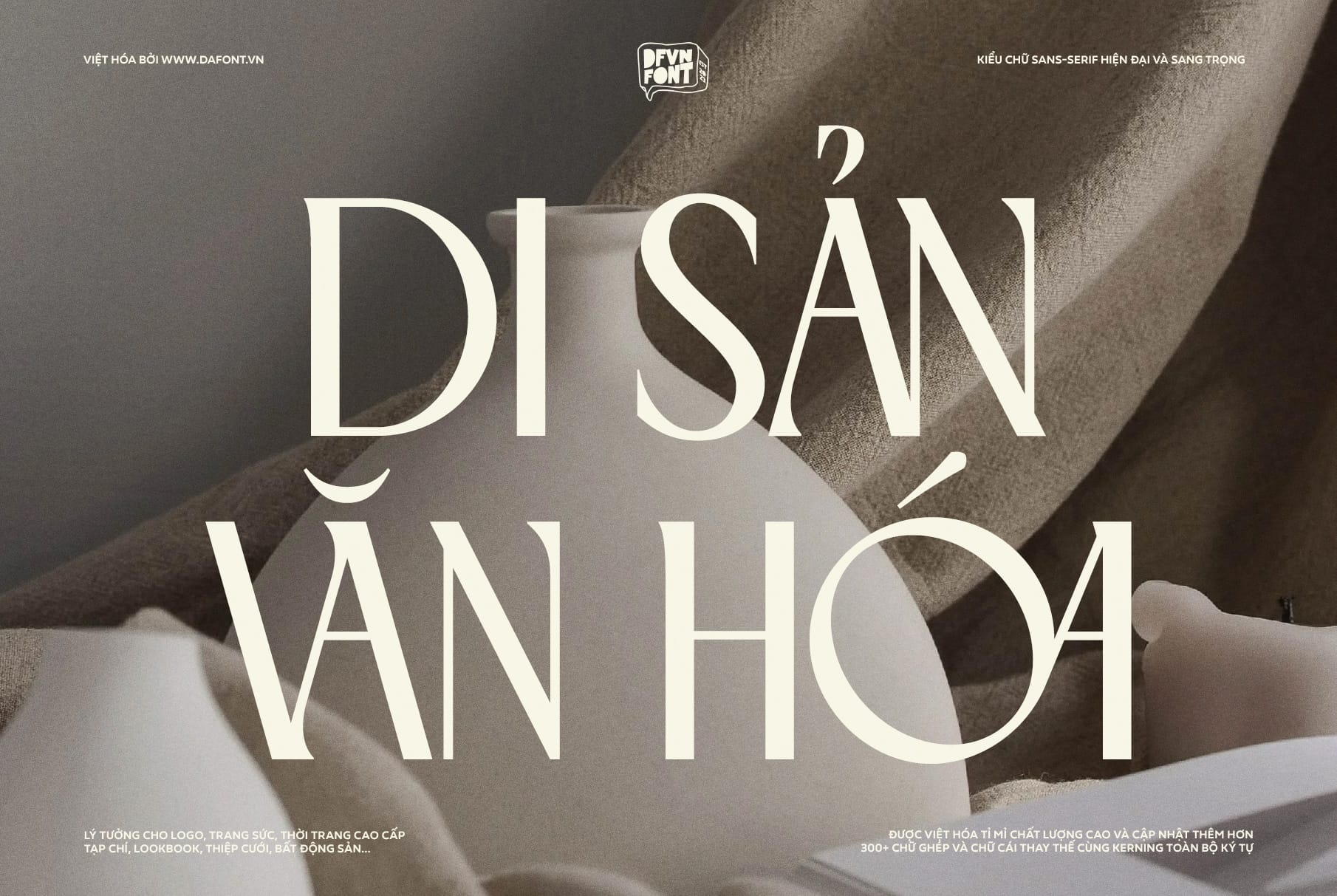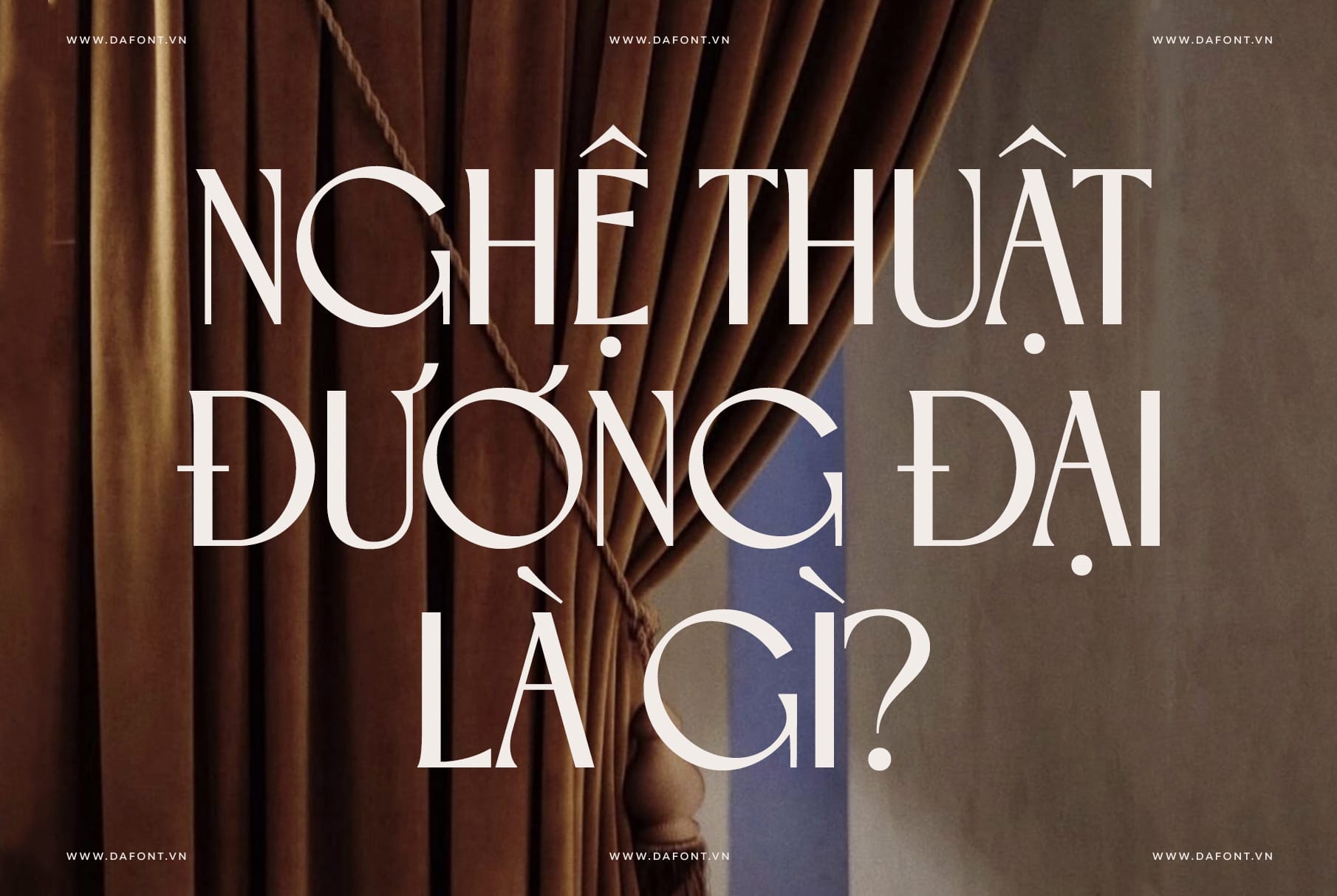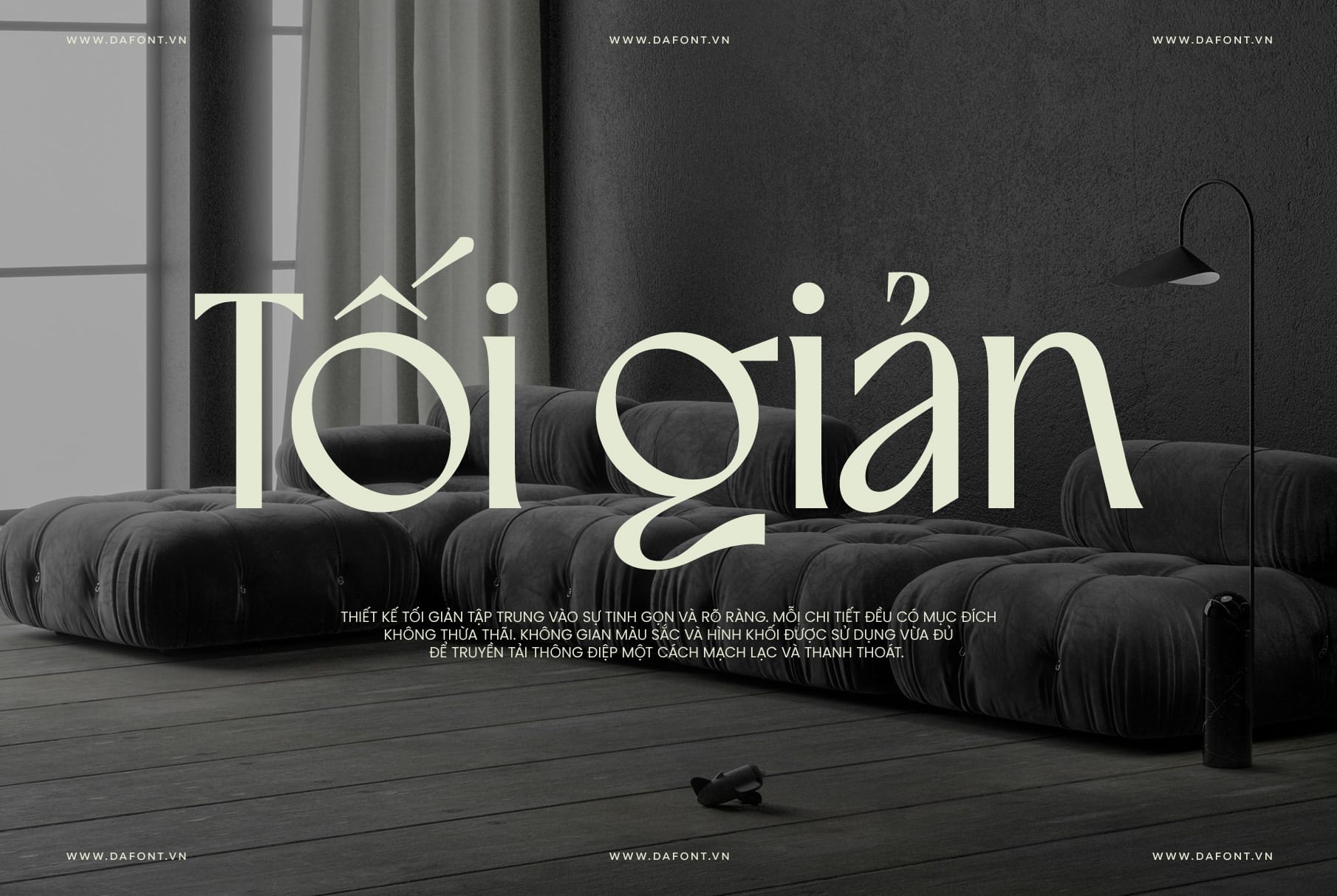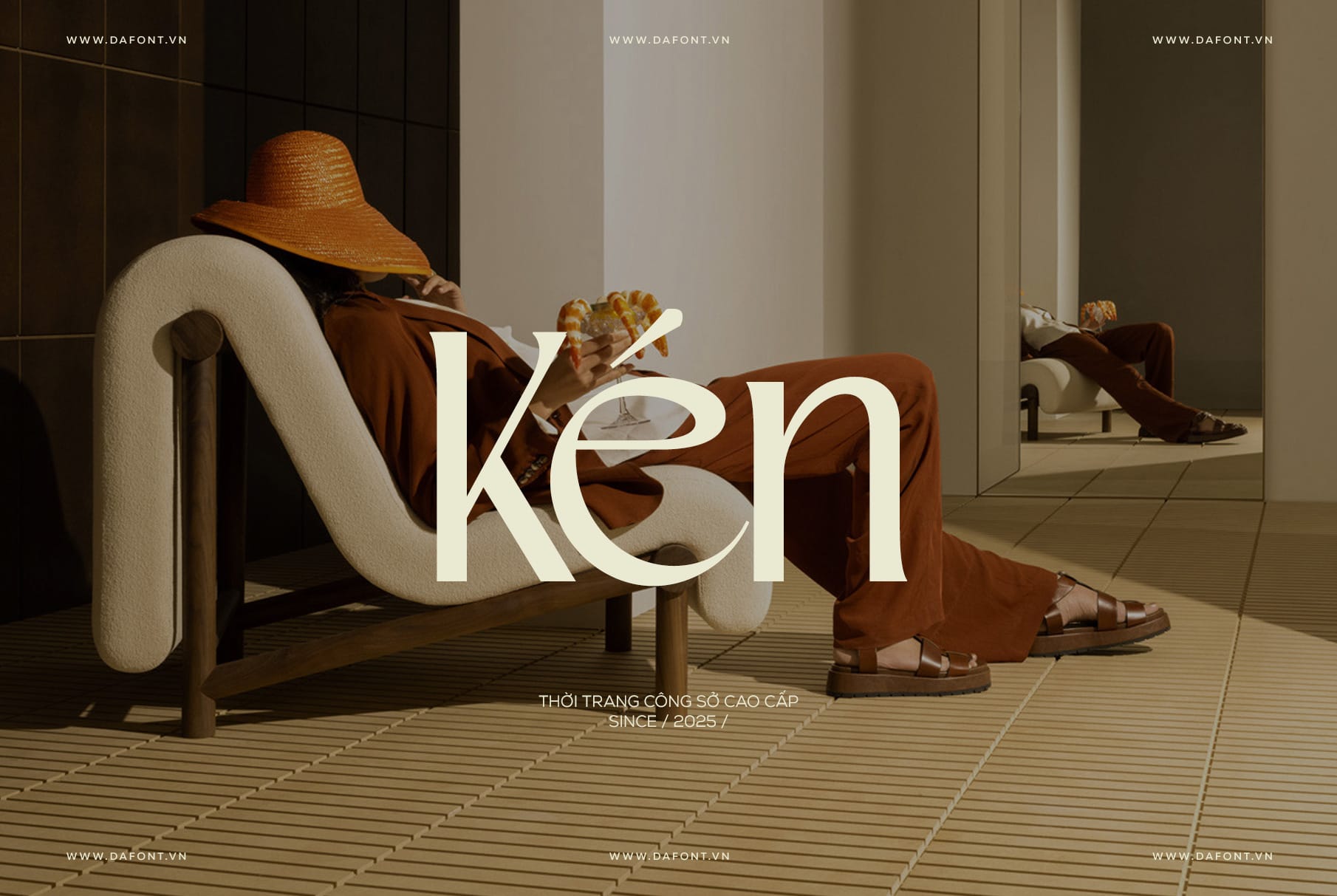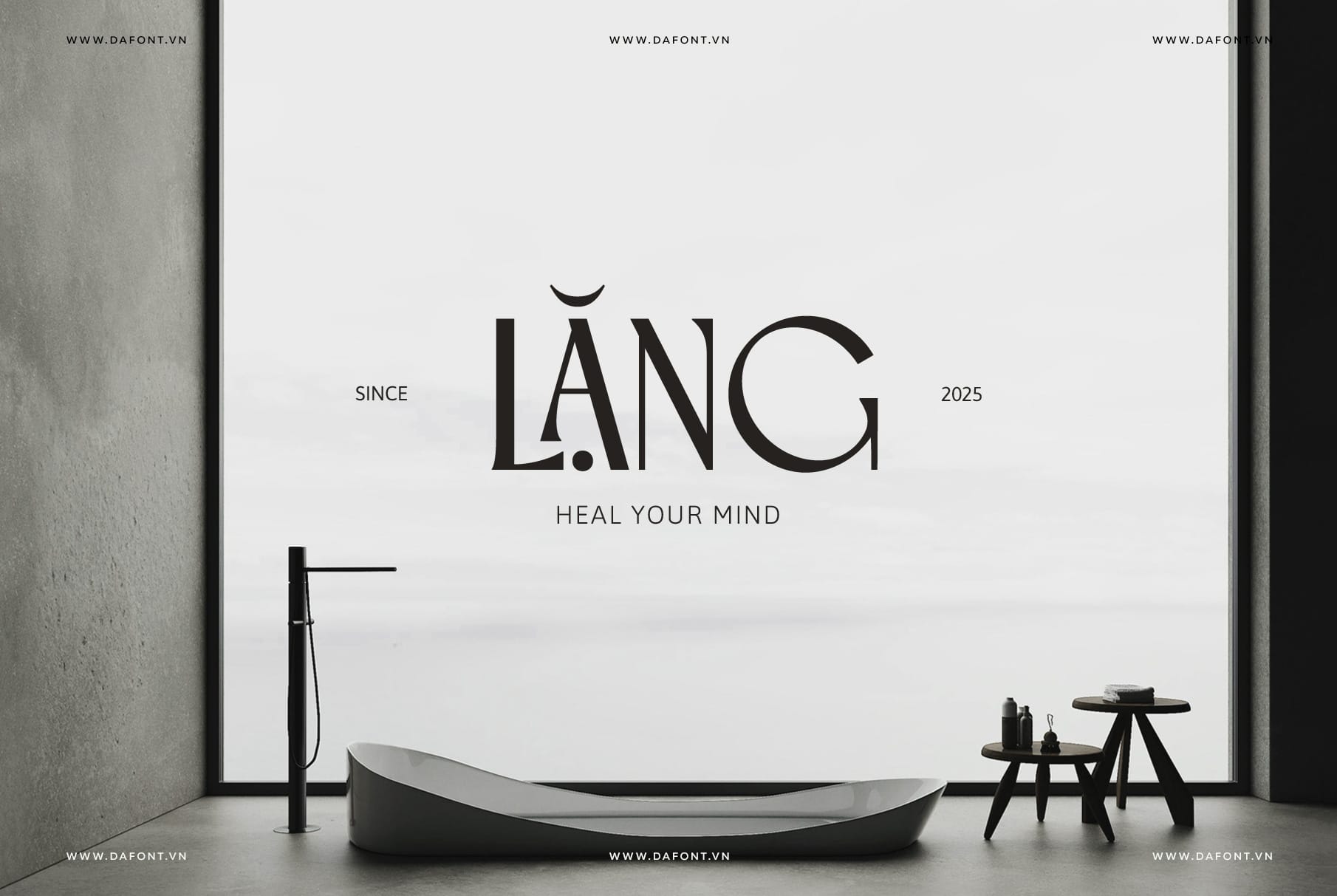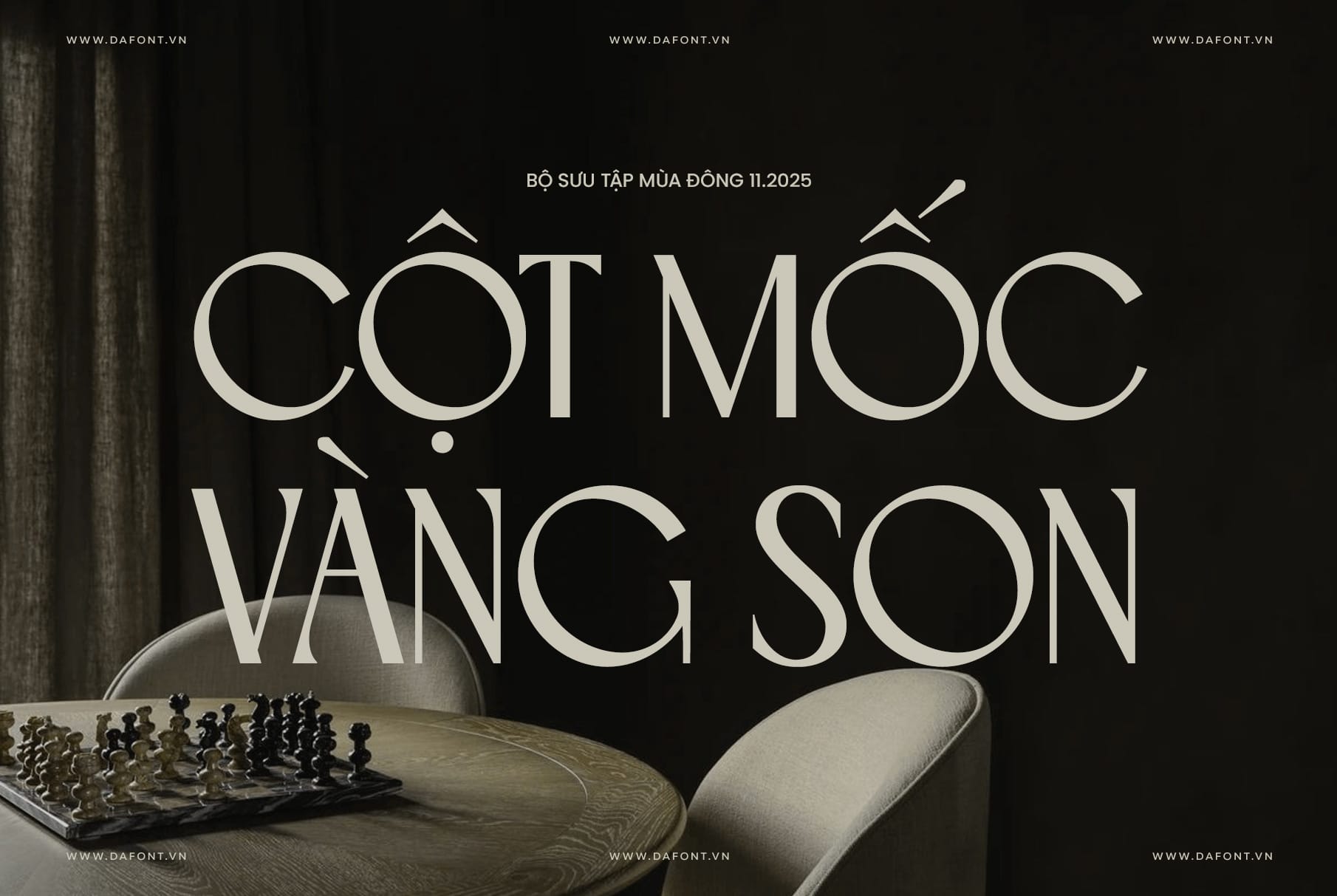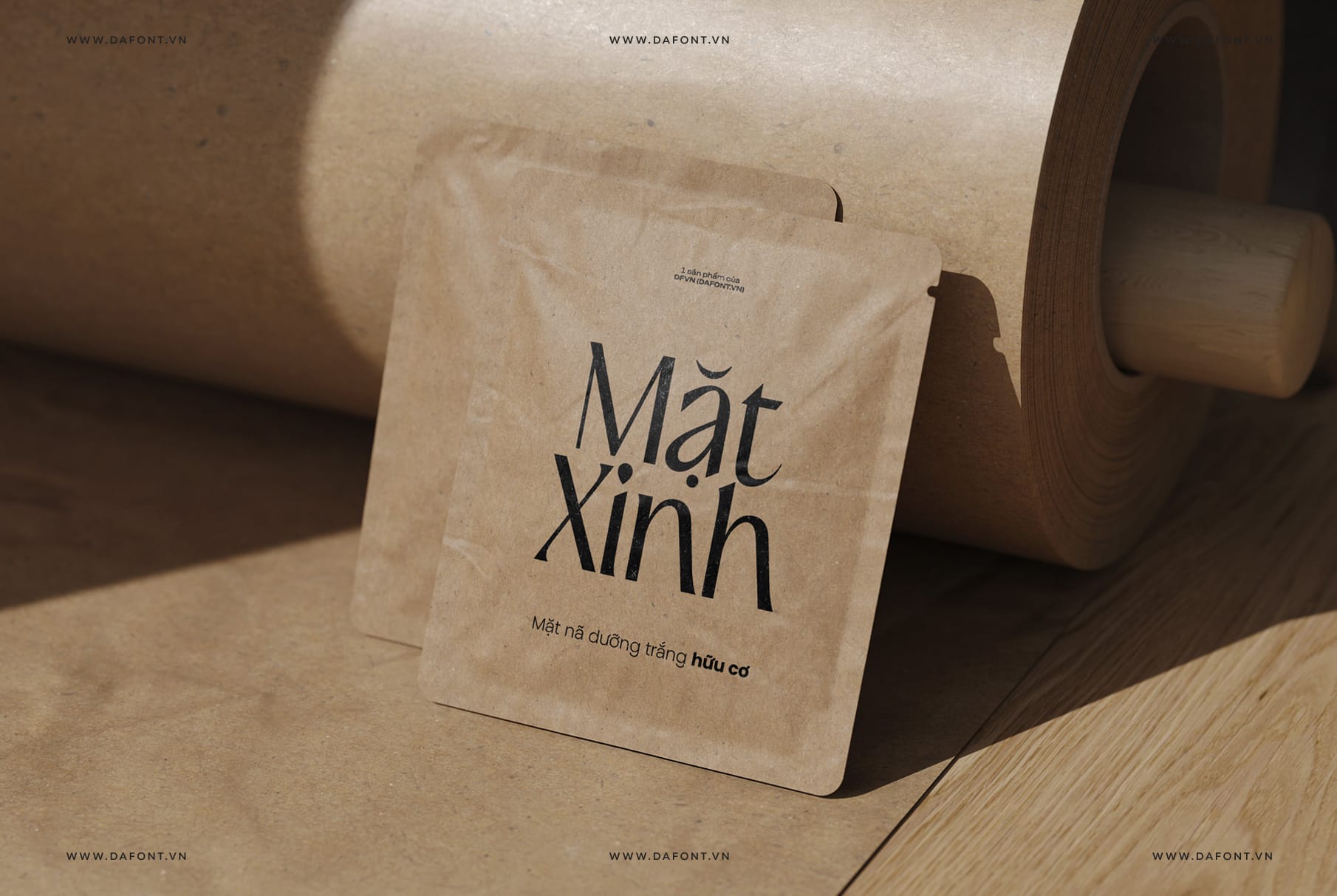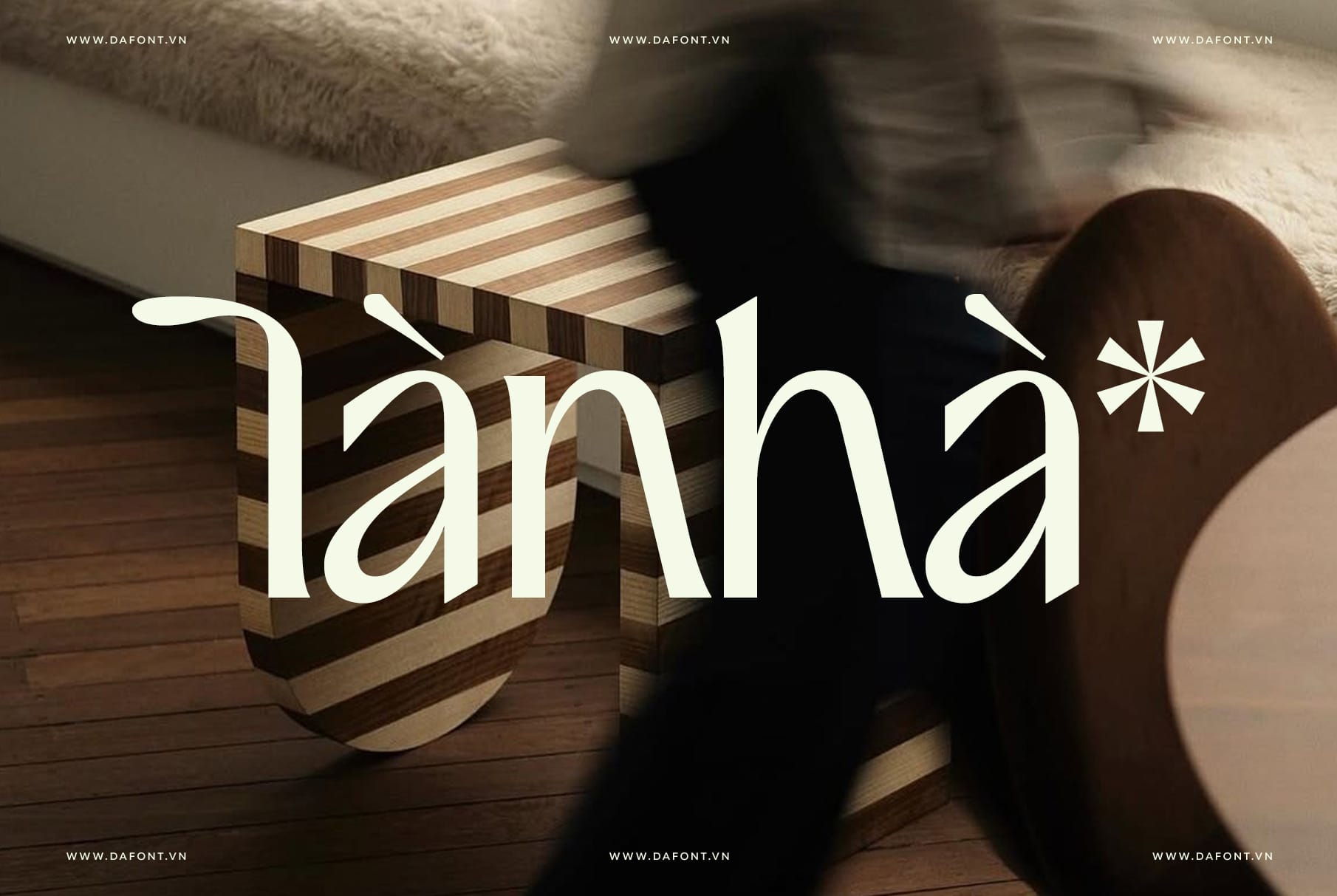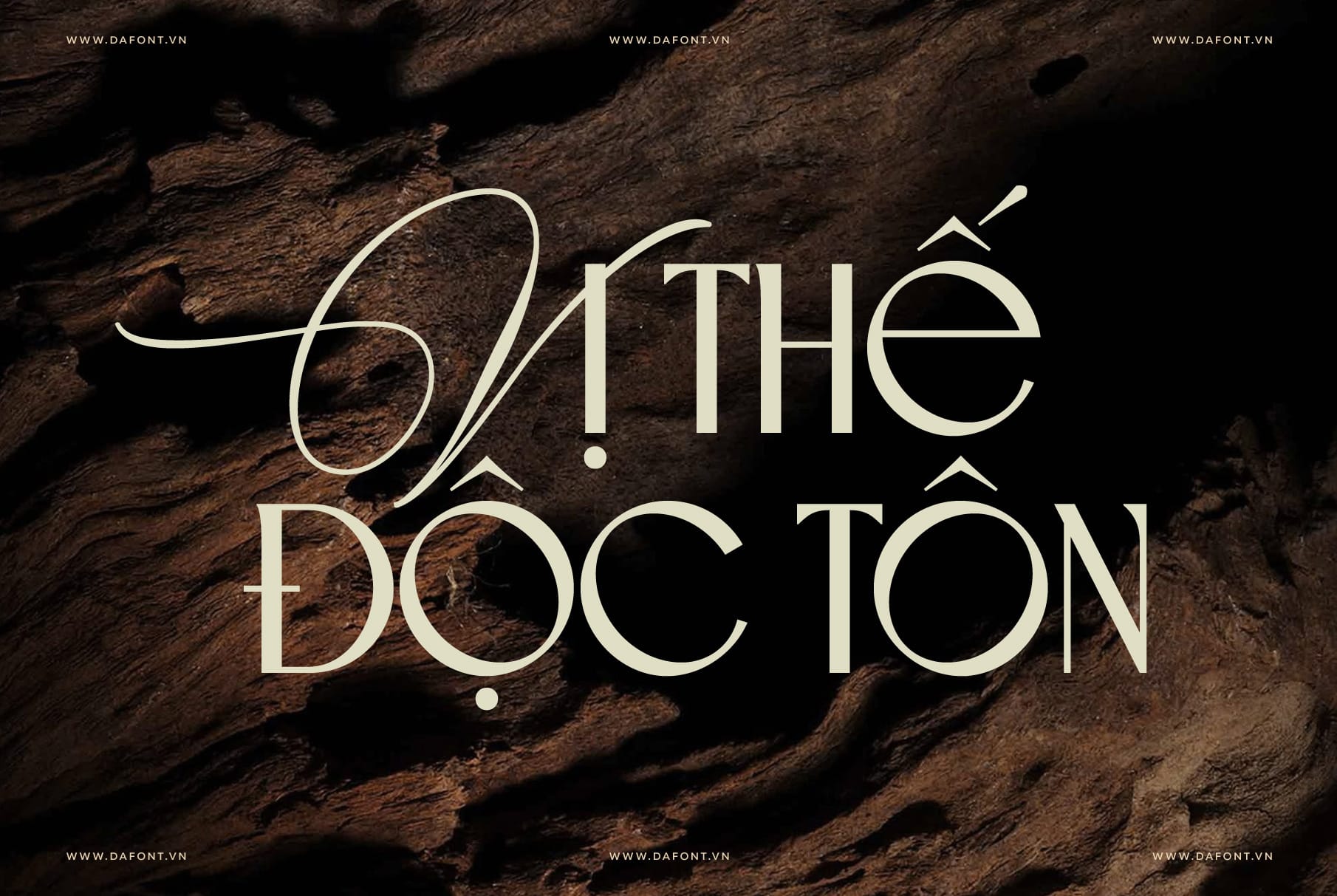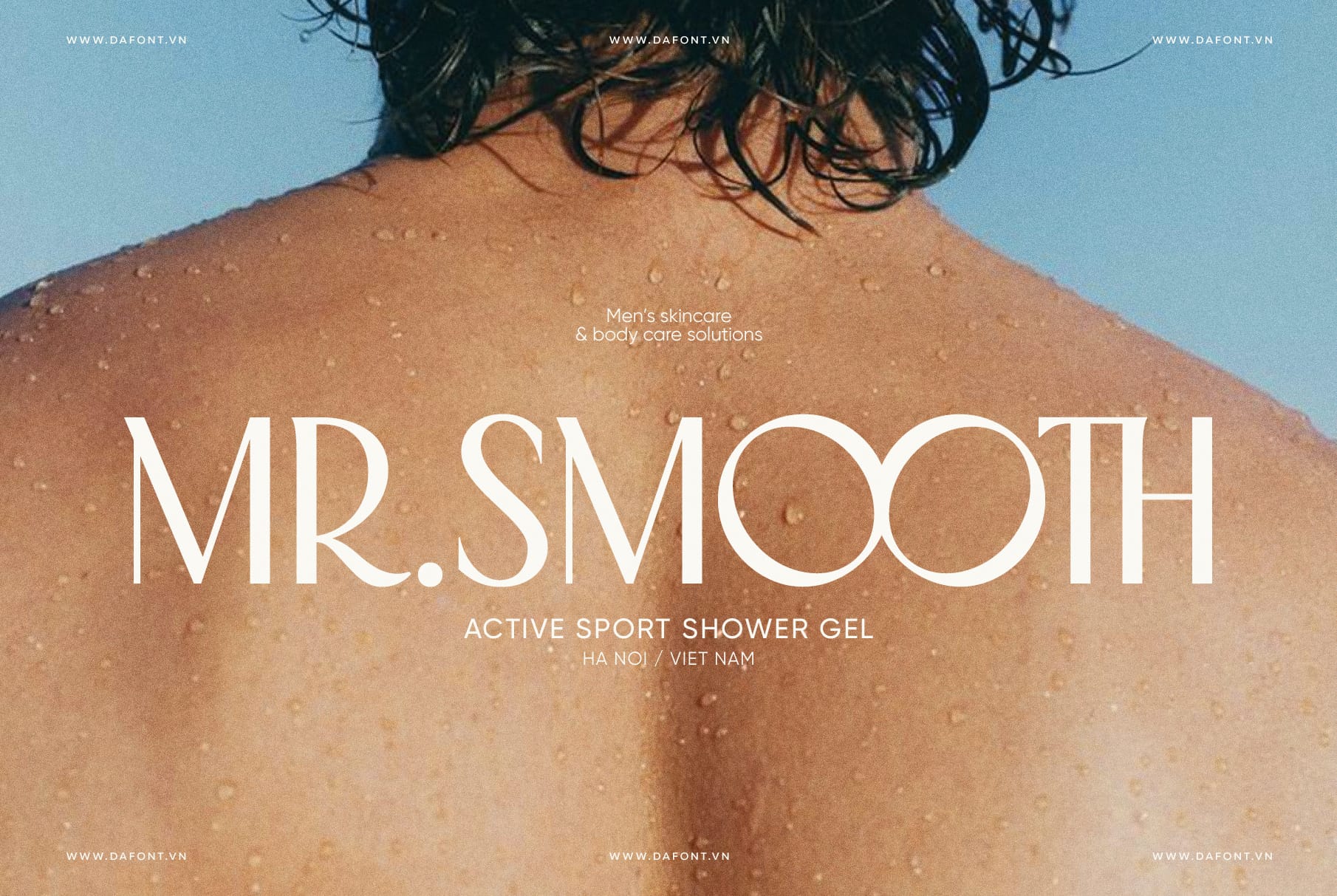
DFVN Soleá là một sans serif typeface kết hợp hoàn hảo giữa thiết kế tối giản, độ tương phản tinh tế và những chi tiết hiện đại, khiến nó trở thành lựa chọn hàng đầu cho các dự án luxury branding, editorial design và logo cao cấp. Với hơn 300+ ligatures, stylistic alternates phong phú và khả năng hỗ trợ đa ngôn ngữ, DFVN Soleá mang đến sự linh hoạt vượt trội, phù hợp cho nhiều dự án thiết kế khác nhau.
Đặc điểm nổi bật DFVN Soleá
1. Tinh thần tối giản nhưng vẫn cá tính
Điểm thú vị của Soleá nằm ở việc nó không cố gắng gây ấn tượng bằng sự ồn ào. Các chữ cái được vẽ với cấu trúc tối giản, tỉ lệ thanh – đậm vừa phải, tạo cảm giác gọn gàng. Tuy nhiên, ở những ký tự như “a”, “e”, “s” hay các chữ có dấu móc, người thiết kế khéo léo đưa vào những đường cong mềm, các chi tiết bất đối xứng nhẹ, khiến font vừa thanh lịch vừa có “cá tính thương hiệu”.
Nhờ đó, DFVN Soleá không bị “lẫn” trong hàng ngàn font chữ sans serif khác trên thị trường, mà vẫn giữ được độ nghiêm túc cần có cho các thương hiệu cao cấp.
2. Hệ thống ligature & stylistic alternates phong phú
Soleá nguyên bản đi kèm hơn 55 ligature và glyph thay thế. Ngoài ra, DFVN đã cập nhât và Việt hóa thêm hơn 300 chữ ghép và biến thể ký tự khác. Đây là yếu tố đặc biệt quan trọng đối với các nhà thiết kế làm việc trong lĩnh vực branding hoặc editorial, bởi vì:
- Bạn có thể tạo logo wordmark độc quyền chỉ bằng cách kết hợp chữ cái với các ligature có sẵn.
- Headline, title tạp chí, bìa lookbook, cover catalogue dễ dàng trở nên “editorial” và giàu tính thời trang hơn.
- Khi sử dụng cho poster hoặc social media, chỉ cần thay đổi một vài glyph là đã có một bố cục mang cảm giác “bespoke” (thiết kế riêng), không giống font hệ thống.
Hệ thống stylistic sets cũng giúp người dùng tùy chỉnh mức độ “phá cách” của font, từ an toàn – tinh gọn cho tới sắc sảo – đậm chất thời trang.
3. Việt hóa chất lượng cao
DFVN Soleá được Việt hóa một cách tỉ mỉ, với hệ thống ký tự được căn chỉnh cẩn thận để đảm bảo tính thẩm mỹ và khả năng đọc tối ưu. Bộ chữ bao gồm hơn 300 ký tự thay thế và chữ ghép đã được Việt hóa đầy đủ, giúp mở rộng tối đa khả năng sáng tạo trong thiết kế. Toàn bộ hệ thống ký tự đều được kerning lại một cách chuyên nghiệp, mang đến trải nghiệm hài hòa và nhất quán ở mọi kích thước và định dạng sử dụng.
DFVN Soleá lý tưởng cho các thiết kế
- Luxury branding & logo thời trang: Soleá rất hợp với thương hiệu thời trang, beauty, lifestyle cao cấp: dùng cho logotype, hệ thống chữ trong bộ nhận diện, tag quần áo, bao bì và logo cho boutique, concept store, showroom nội thất tối giản.
- Editorial & magazine layout: Với tỷ lệ chữ đậm chất editorial, Soleá lý tưởng cho cover, headline tạp chí, tiêu đề chuyên mục, lookbook, catalogue và portfolio. Kết hợp Soleá cho heading cùng một serif nhỏ cho body text sẽ tạo vibe tạp chí thời trang quốc tế.
- Packaging & bao bì tối giản: Soleá phù hợp bao bì tối giản cho đồ uống, skincare, home fragrance, F&B cao cấp: logo trên hộp/chai/lọ, tên sản phẩm và các thông tin chính trên front label.
- Website & giao diện số: Soleá thích hợp dùng cho heading và khối nội dung nổi bật trên website, landing page thương hiệu, portfolio cá nhân và blog thời trang/lifestyle mang phong cách editorial.
- Stationery & ấn phẩm in: Soleá hoạt động tốt trên các ấn phẩm in: thiệp mời, letterhead, phong bì, bất động sản, danh thiếp, poster cho cửa hàng, showroom, gallery, giúp hệ thống nhận diện tổng thể đồng bộ và sang trọng.
Kết luận
Tóm lại, DFVN Soleá không chỉ là một kiểu chữ sans serif hiện đại, mà còn là một công cụ xây dựng hình ảnh thương hiệu đầy hấp dẫn. Sự kết hợp giữa tinh thần tối giản, chi tiết tinh tế, hệ thống ligature và ký tự thay thế phong phú. Từ luxury branding, logo thời trang, editorial design cho đến bao bì tối giản và giao diện số.